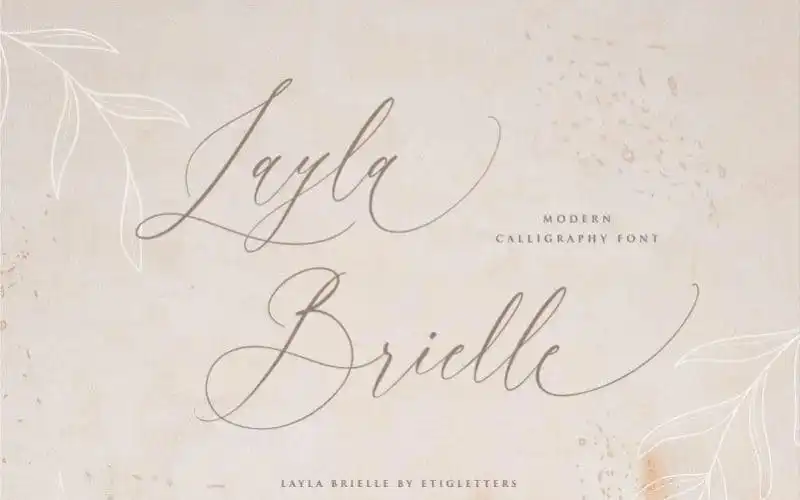
Layla Brielle Calligraphy Font
A fonte ‘Layla Brielle Calligraphy Font’ é uma elegante escolha para designers e criativos buscando um estilo delicado e sofisticado. Desenvolvida pelo designer etigletters, essa tipografia script perfeita combina elementos de elegância com sutileza, tornando-a ideal não apenas para cartões de casamento e convites, mas também para personal branding e criação de identidade visual que exige um toque delicado. Com seu ar refinado, a ‘Layla Brielle Calligraphy Font’ é perfeita para quem busca unir elegância com uma dose de modernidade no design gráfico, seja em cartões de felicitações ou materiais promocionais pessoais. Englobando o mundo da personal branding, essa fonte não apenas adiciona um toque especial ao seu trabalho, mas também é uma ótima escolha para marcas e identidades digitais que buscam expressar sua individualidade de maneira sofisticada.